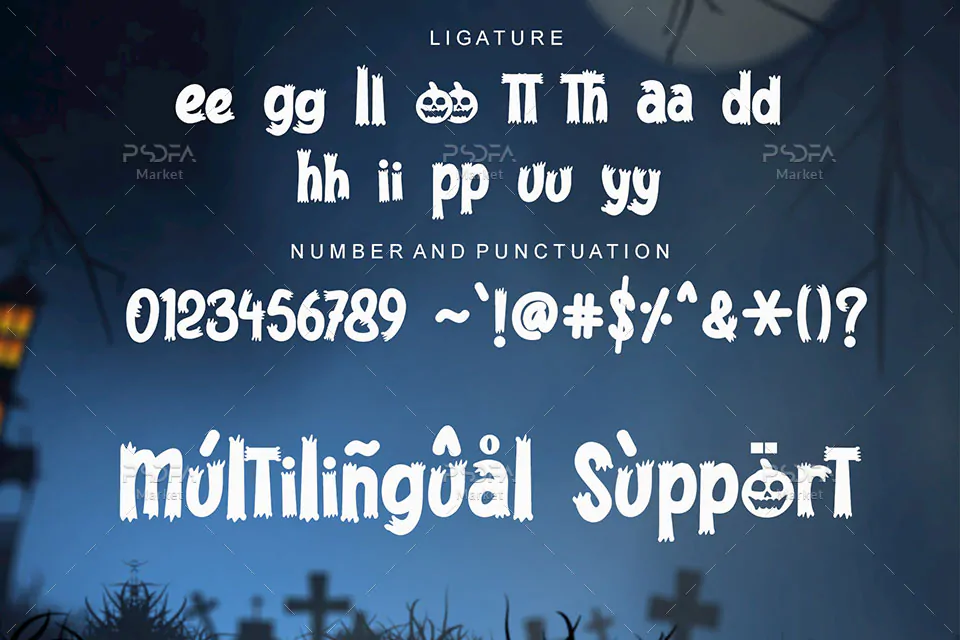
فونت ترسناک ارواح و شبح Spooky Hunter
فونت ترسناک ارواح و شبح
فونت ترسناک ارواح و شبح Spooky Hunter یک قلم نمایشی با کاراکترهای ضخیم است که مناسب جهت استفاده در طرح و پروژههای گرافیکی مختلف میباشد. این قلم انگلیسی در قالب فایلهای otf, ttf در فایل محصول قرار دارد که پس از نصب آن در پوشه فونتهای سیستم میتوانید در نرم افزارهای مختلف از این فونت زیبا استفاده کنید.
فونت Spooky Hunter در دو وزن معمولی و مورب طراحی شده است که میتوان از آن در طراحی انواع کارت تبریک، کارت پستال، بنر، پوستر، تراکت، بسته بندی محصولات، ظروف یکبار مصرف، تقویم، پارچه و لباس، لوازم التحریر و … استفاده نمود.
- وزن: Regular, Italic